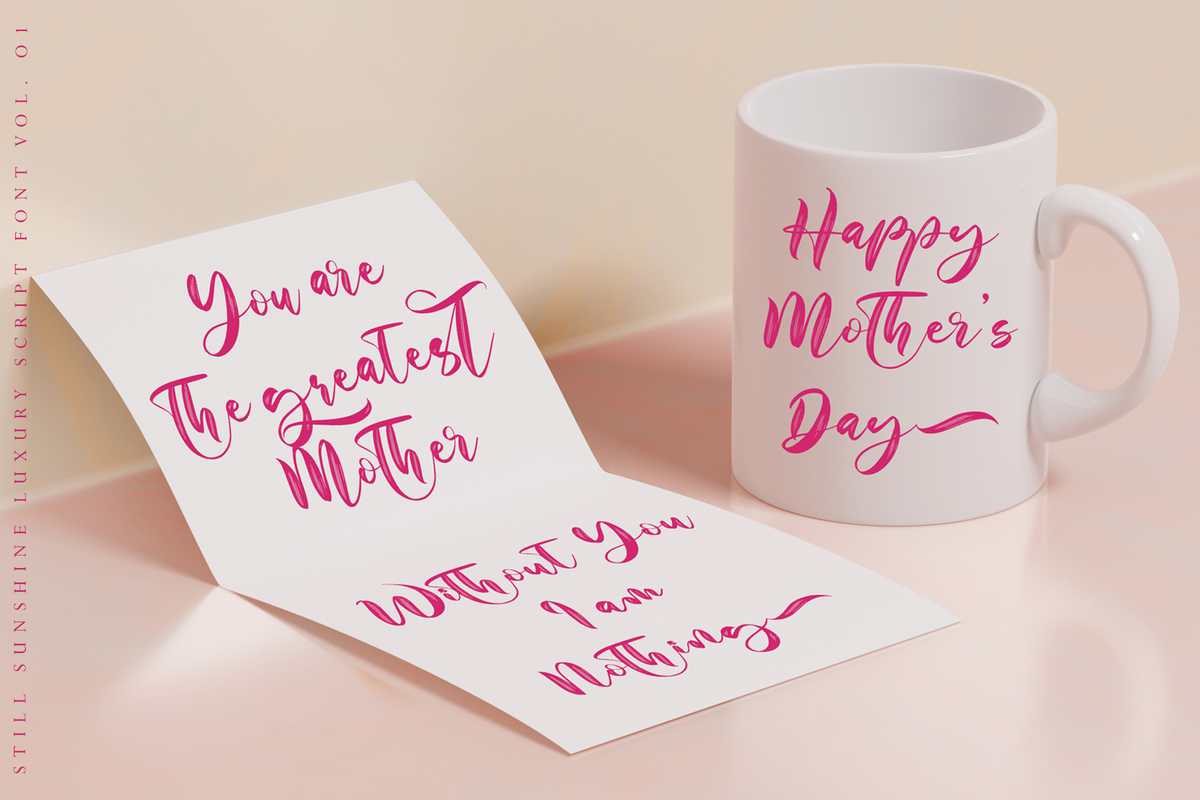
Stills Sunshine是一款甜美、全面、灵活的手写字体。热情、浪漫、愉悦,这款字体将让您的每一个项目都变成艺术作品。Stills Sunshine是一款编码为,意味着您可以访问字形和Swashease!Stills Sunshine是一款甜美、全面、灵活的手写字体。热情、浪漫、愉悦,这款字体将让您的每一个项目都变成艺术作品。Stills Sunshine是一款编码为,意味着您可以访问字形和Swashease!